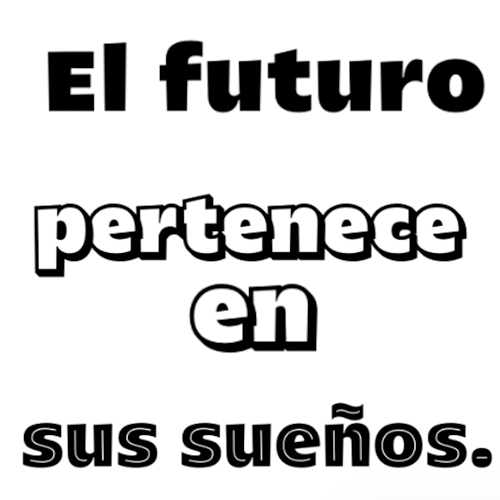
Kiara Black
| Descripción | Kiara es una versión mejorada de "Laika" en esta fuente contiene 4 estilos para usar juntos, contiene el alfabeto cirílico, ligaduras y muchas alternativas, especialmente para títulos grandes |
| Familia(s) | Kiara Black Regular, Kiara Black Regular Shadow, Kiara Black Regular Inline |
| Estilos | 4 |